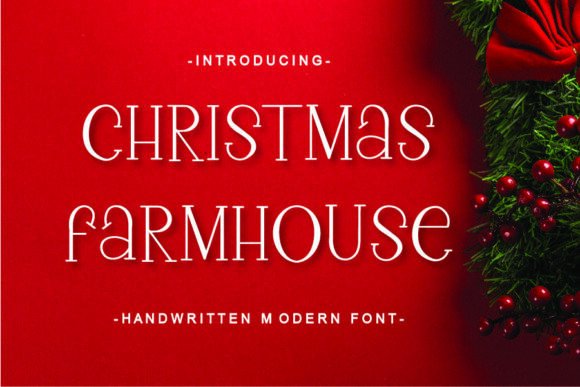
Christmas Farmhouse
適切なデザイン要素を見つけるのは難しい場合がありますが、Christmas Farmhouseは作品を即座に引き立てる優れたコレクションを提供します。
精密に作られたChristmas Farmhouseは、クリーンなベクター、滑らかなタイポグラフィ、そして安心のための商用ライセンスを提供します。
POD(オンデマンド印刷)製品、結婚式の招待状、またはソーシャルメディアのグラフィックを作成している場合でも、Christmas Farmhouseは理想的です。